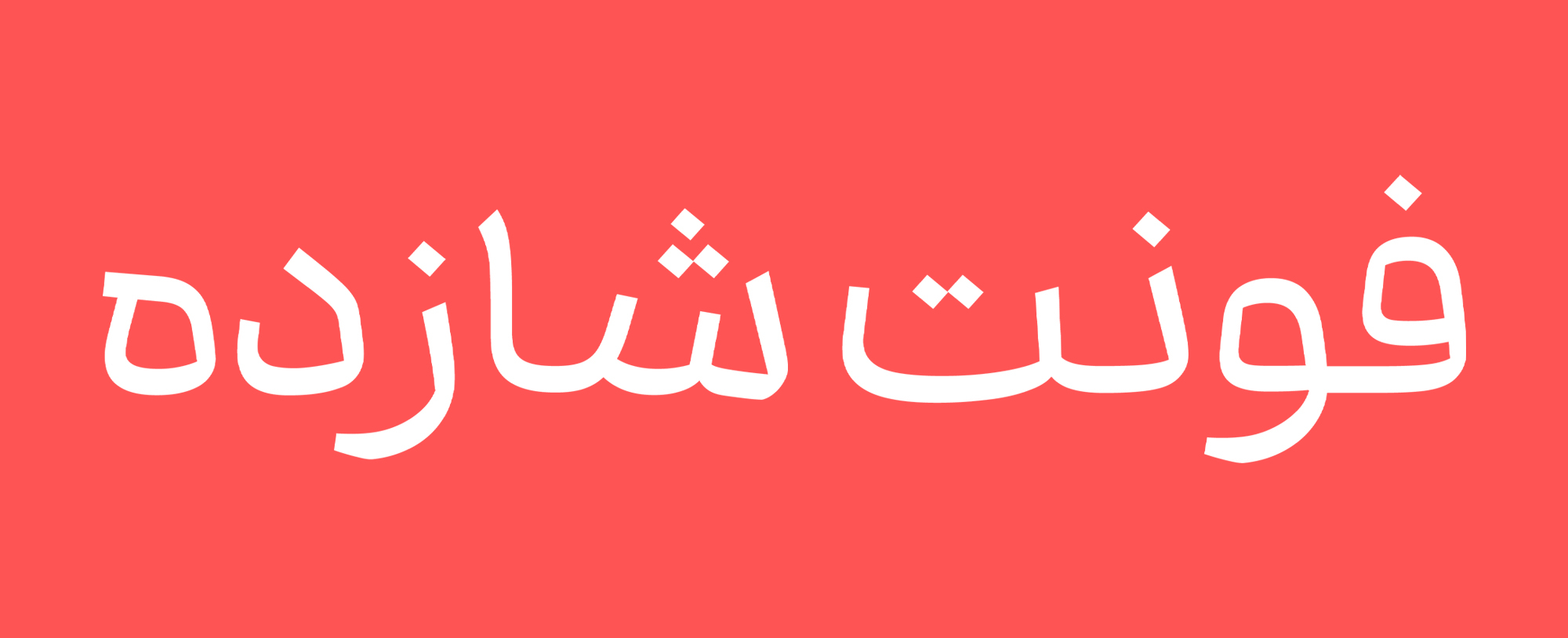
فونت شازده
شازده، یک تایپ‌فیس مدرن فارسی _ عربی است که به‌صورت ویژه برای کاربردهای دیجیتال طراحی شده است. از ابتدا تمرکز آن بر وضوح، خوانایی و عملکرد بالا در محیط‌هایی مانند وب‌سایت‌ها، رابط‌های کاربری، اپلیکیشن‌ها و متن‌های طولانی بوده است. شازده حتی در اندازه‌های بسیار کوچک، کیفیت بصری خود را حفظ می‌کند و بدون افت وضوح، تجربه‌ای روان و خوش‌خوان ارائه می‌دهد.
در روند طراحی، حروفی مانند «الف» و «لام» با ارتفاعی کوتاه و کنترل‌شده اجرا شده‌اند. این تصمیم باعث شده تا فضای عمودی متن فشرده‌تر شود و تراکم خطوط کاهش یابد، بدون آنکه به خوانایی لطمه‌ای وارد شود. همین ویژگی، متن را در نمایشگرهای کوچک یا تراکم‌های بالا (High-DPI) خواناتر و کاربردی‌تر می‌کند.
فرم کلی حروف با ساختاری نزدیک به مونولاین طراحی شده است؛ ترکیبی دقیق از نرمی خط، تعادل هندسی و تأثیرپذیری هوشمندانه از ساختار خط نسخ. هر گلیف به‌گونه‌ای طراحی شده که در محدوده‌ی خود به‌خوبی قرار گیرد، و این دقت، چیدمان متن را در سیستم‌های مبتنی بر گرید منظم و سازگار نگه می‌دارد.
در نتیجه، فونت شازده نه‌تنها در اندازه‌های ریز عملکردی عالی دارد، بلکه در متن‌های بلند، مقالات دیجیتال و رابط‌های کاربری پیچیده نیز ظاهر ساختارمند، یکدست و حرفه‌ای خود را حفظ می‌کند. تلفیق زیبایی‌شناسی معاصر با اصول سنتی تایپوگرافی فارسی و عربی، شازده را به انتخابی مطمئن برای طراحان وب، توسعه‌دهندگان رابط و ناشران دیجیتال تبدیل کرده است.